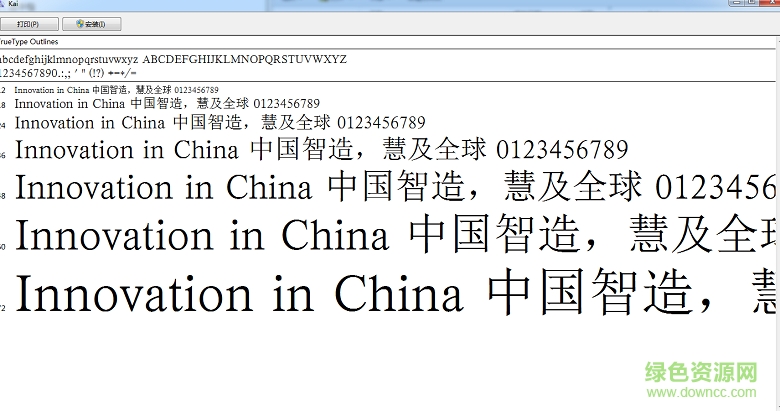
sil-kai-reg-jian字體是一款風(fēng)格典雅的楷書字體,筆形柔和,筆畫雅致,外形清秀俊朗,極具美感,閱讀效果好,喜歡這款字體的朋友快來下載收藏吧!
非常經(jīng)典,經(jīng)過一千多年文明和無數(shù)書法大師的不斷錘煉,已經(jīng)非常成熟了,每一個(gè)字都經(jīng)得起推敲,具有很強(qiáng)的文化氣質(zhì),因此在做具有文化感和傳統(tǒng)味的設(shè)計(jì)中常用!